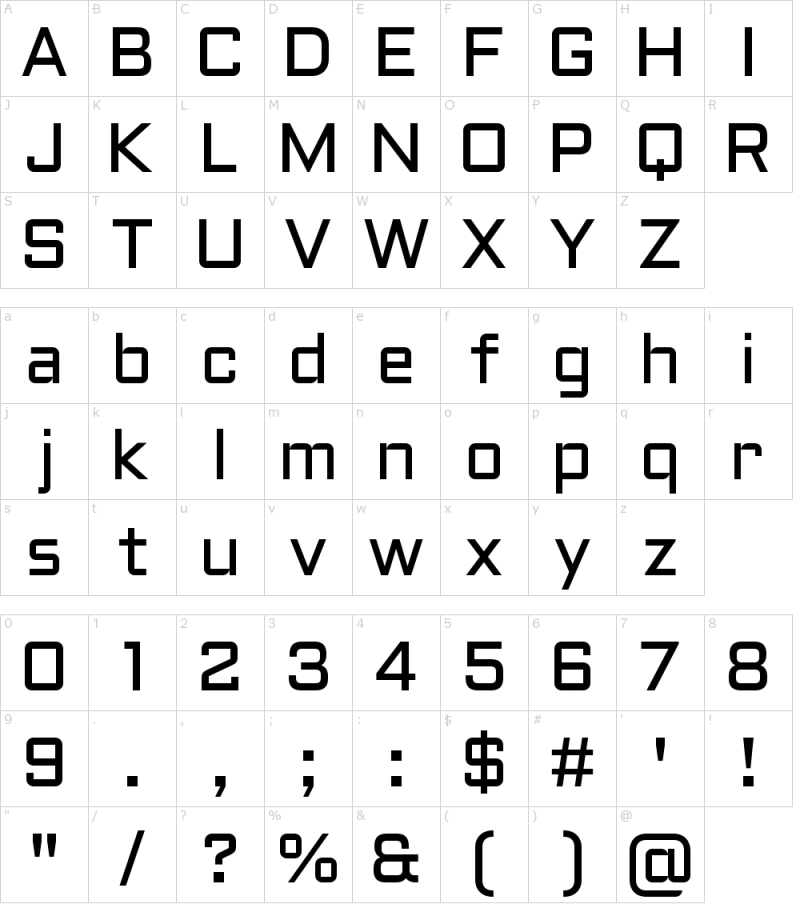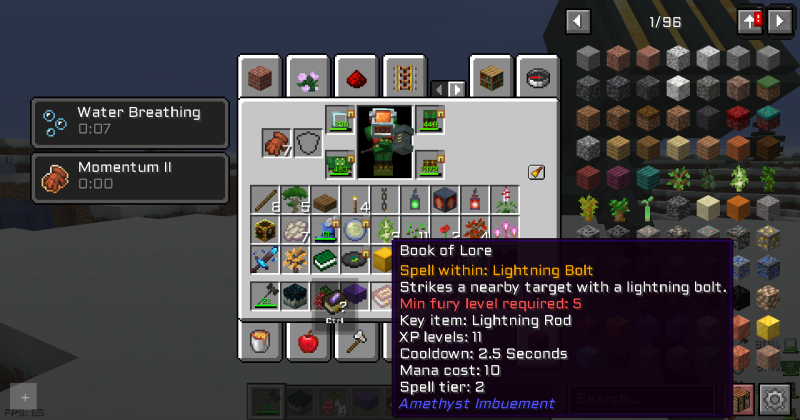
Tech RPG Font 26.3/1.21.11 (Современный технологичный шрифт 32x)
Tech RPG Font предлагает игрокам уникальный визуальный опыт, заменяя стандартный шрифт Minecraft на современный и чёткий технологичный шрифт. Стиль напоминает элементы из RPG-игр, придавая интерфейсу игры более продвинутый и футуристический вид. Шрифт отличается высокой детализацией и лёгкой читаемостью, что делает его идеальным для длительных игровых сессий.
Основанный на популярном шрифте Aldrich от MADType, этот текстурпак сохраняет все лицензионные требования Open Font License. Изначально созданный для модпака DarkRPG, теперь он доступен всем игрокам, желающим освежить визуальную составляющую своего Minecraft-опыта. Шрифт не добавляет новых игровых механик, а лишь меняет эстетику текста, сохраняя атмосферу игры.
• Чёткий и современный технологичный дизайн шрифта
• Улучшенная читаемость текста в интерфейсе игры
• Стиль, вдохновлённый RPG-играми